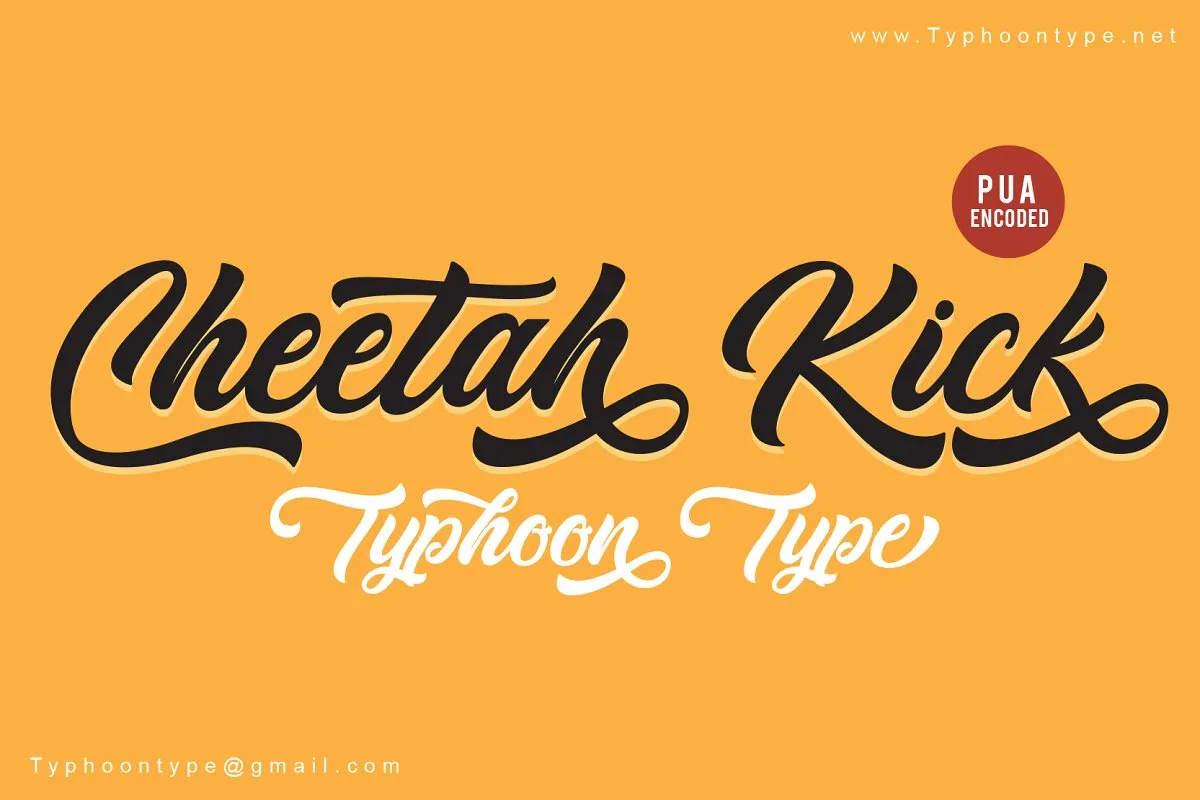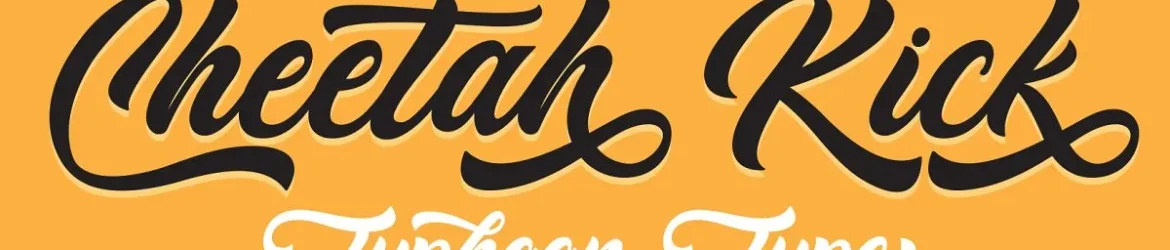
Cheetah Kick Script Font – Download Grátis
A Cheetah Kick Script Font é uma escolha perfeita para quem busca dar um toque sofisticado aos seus projetos digitais sem precisar de ferramentas adicionais. Este estilo elegante e criativo permite que você transforme qualquer tipo de texto em designs incríveis, desde logomarcas e tags personalizadas até embalagens de produtos, roupas e cartões de aniversário. Com múltiplas características do tipo opentype como ligatura, alternativas estilísticas, alternativas contextualas, swashes e suporte a várias línguas, esta fonte é perfeita para quem deseja um acabamento único em qualquer projeto. Estamos convencidos de que ela irá transformar seu trabalho em algo realmente especial. Não hesite em explorar as possibilidades criativas desta fonte única.